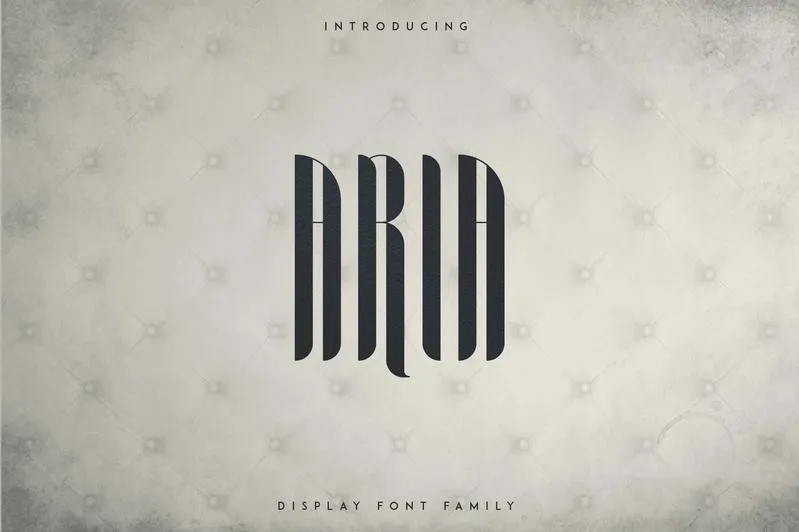
Aria Display Font Family – Download Grátis
Aria Display é uma família de fontes display elegante e longa com quatro tipos diferentes, oferecendo suporte a múltiplas línguas. Ela destaca-se como um tipo poderoso que se adapta perfeitamente tanto para grandes tamanhos quanto para menores detalhes. Ideal para aplicação em gráficos visuais imponentes e design de escritório digital, Aria Display é uma fonte versátil que adicionará um toque inconfundível a qualquer projeto, seja ele no formato impresso ou digital. Com sua ampla gama de usos, esta família de fontes certamente se tornará um dos seus queridinhos para trabalhos de design gráfico profissional. Aria Display é uma fonte que não apenas compreende idiomas em várias línguas, mas também traz alegria e diversidade à sua biblioteca personalizada.